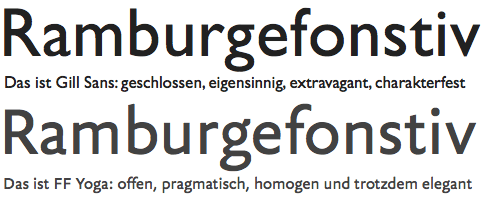
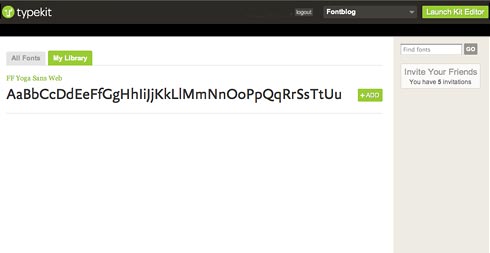
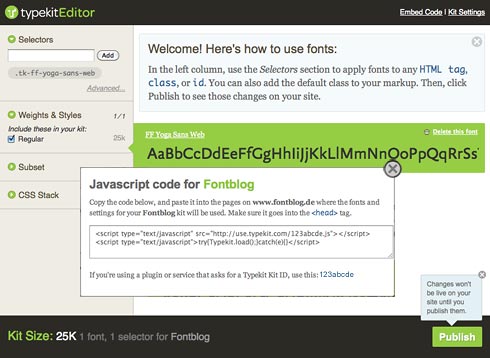
Wie Ihr alle schnell mit einem Browser ≠Firefox 3.6 oder IE feststellen könnt, erscheinen das Fontblog-Logo, die -Headlines und die -Seitenleiste in FF Yoga Sans.
so als bildschirmschrift finde ich die yoga nicht schön. da kommt einen ff din oder meta besser weg. oder ihr macht die schrift etwas größer, denn leider gehen bei der jetzigen größe die details der schrift unter.
@robertmichael: Es ist sicher nicht die beste Wahl für Lesegrößen oder Microtexte, aber ich wollte sie einfach mal ausprobieren. Wahrscheinlich werde ich immer wieder mal wechseln … darf ich mir ja erlauben :-), als Schriftverkäufer.
Jens, umstricken kann ich sie mir auch selbst, aber das ist ja nicht der Sinn der Übung. Ich find das bei Typotheque im Ansatz gut gelöst, da kannst du die OTF kaufen und modelst dir «deine» Version, indem du dich für Ziffern usw entscheidest, und fertig. Ich finde die Begründung für Versalziffern auch nach wie vor seltsam – auch die Meta sieht damit einfach nicht gut aus. Was im Print bessere Lesbarkeit ausmacht gilt am Bildschirm nicht mehr?
Es ist auch nicht erlaubt, HD!
Die Typkit-Geschichte funktioniert weder mit Opera 10.20 noch mit Opera 10.51 (rc3).
Opera 10.x selbst unterstützt zwar @font-face, nicht aber die Formate EOT und WOFF. Und der Typkit-Fallback funktioniert offenbar ebenfalls nicht.
[In Zeile 481 des Styledheets themes/fontblog_2010/style.css übrigens gehört das Komma mit auskommentiert! ;)]
Das Opera-Problem ist bei Typekit hinlänglich bekannt, und sie arbeiten dran. Seit geraumer Zeit. ;-)
Mehr schlecht als recht kommt man auch – stellte ich fest – mit Opera 10.x in den Genuss der Webfonts, wenn man „Mask as Firefox“ für die betrachtete Site aktiviert.
Sieht man sich das Typekit-Script deweirdified an, stellt man fest, dass da – nach erstem Augenschein beurteilt, jedenfalls – viel zu viel unnötiges Browsersniffing betrieben wird.
@ jürgen >immer wieder mal wechseln
Und wie entscheidende Leute bei Opera zum thema Webfonts stehen, weiß ich leider nicht genau, und ich kann leider auch nicht beurteilen, wie ‹entscheidend› Håkon Wium Lie ist, als CTO, aber den Text von Jeffrey Zeldman hast Du ja vermutlich auch gelesen bzw weißt über die Geschichte bestimmt besser Bescheid als ich ;-) «In August, 2007, CSS co-creator and Opera Software CTO Håkon Wium Lie wrote CSS At Ten, reminding us that CSS provided a mechanism by which actual font files could be linked to and retrieved from the web. Soon after the article was published, “web fonts” discussions started popping up».